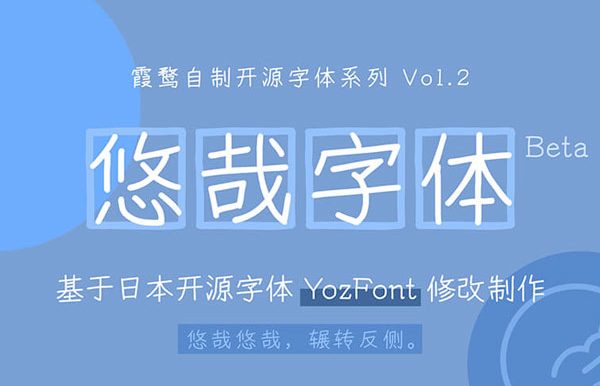
一款基于免费开源的手写风格字体 – 悠哉字体
悠哉字体(Yozai Font)是一款基于免费开源的Y.OzFont(日本)的手写风格的字体,作者是中国大陆的落霞孤鹜。目前已补全原字体中有对应繁体字的简体字,并补全了4808常用繁体中文汉字,以及3500常用简体中文汉字。 4808 常用繁体中文汉字是指台湾教育部门规定的 4808 个常用汉字。3500常用简体中文汉字是指《现代汉语常用字表》规定的 3500 个常用汉字。- 4.9k
悠哉字体